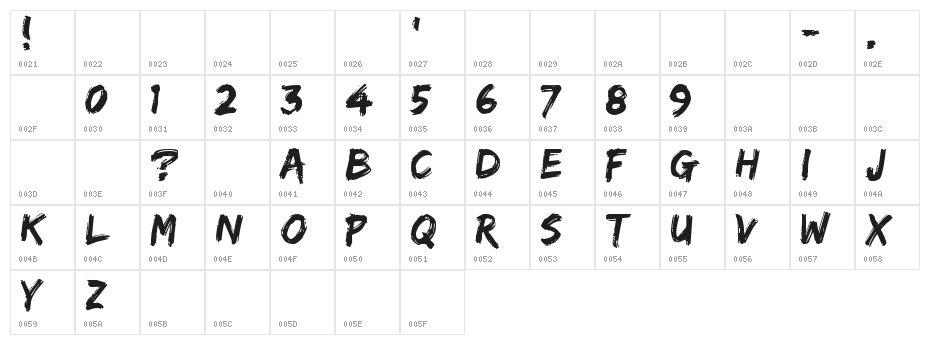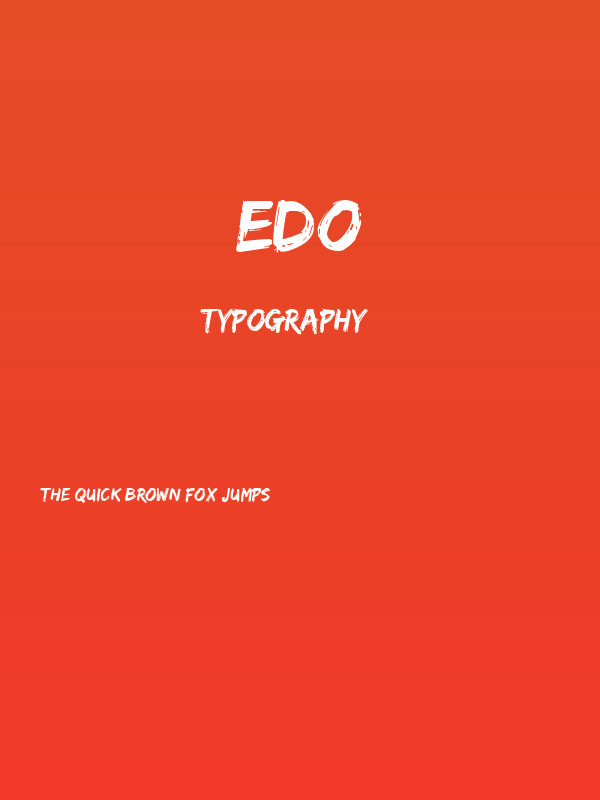
Edo Font
| Gesamtstil | Modern, Artistic |
| Vorgeschlagene Projekte | Ideal for posters, album covers, branding, and any creative projects needing a bold, artistic touch. |